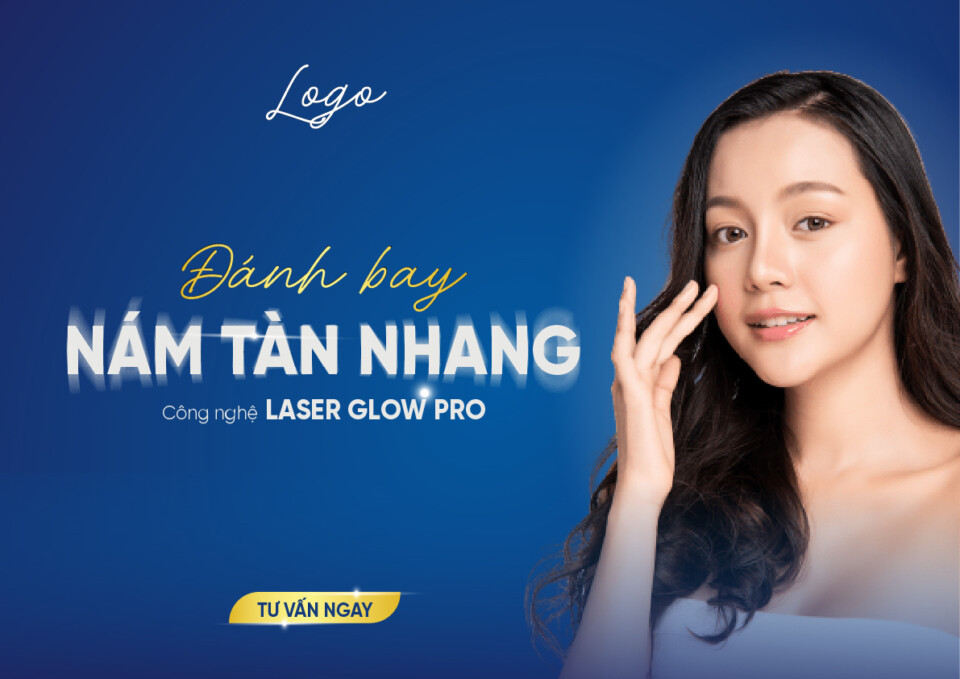
Combo font chữ Spa 1 kèm hiệu ứng đẳng cấp cho thiết kế ngành làm đẹpSức hút từ bộ Combo font chữ Spa 1 kèm hiệu ứng trong thiết kế hiện nayTrong ngành dịch vụ làm đẹp và chăm sóc sức khỏe tại Việt Nam, việc xây dựng hình ảnh thương hiệu chuyên nghiệp là yếu tố sống còn để thu hút khách hàng tiềm năng. Một Font Miễn Phí phù hợp không chỉ đơn thuần là công cụ hiển thị văn bản mà còn là ngôn ngữ thị giác truyền tải sự tinh tế và sang trọng. Chính vì vậy, Combo font chữ Spa 1 kèm hiệu ứng đã trở thành giải pháp tối ưu dành cho các nhà thiết kế đồ họa cũng như chủ doanh nghiệp muốn tạo nên sự khác biệt. Bộ sưu tập này được tuyển chọn kỹ lưỡng, tập trung vào các nét chữ thanh mảnh, bay bổng nhưng vẫn giữ được sự hiện đại cần thiết cho các ấn phẩm như menu spa, card visit, hay biển hiệu quảng cáo ngoài trời.Lý do nên lựa chọn font chữ Việt hóa cho ngành làm đẹpVấn đề lớn nhất khi sử dụng các bộ chữ quốc tế chính là lỗi hiển thị tiếng Việt, đặc biệt là các dấu thanh đặc trưng. Với Combo font chữ Spa 1 kèm hiệu ứng, mọi rào cản về kỹ thuật đã được loại bỏ hoàn toàn nhờ quá trình Việt hóa tỉ mỉ. Các đường nét được căn chỉnh sao cho dấu câu không bị đè lên chữ, giữ nguyên tính thẩm mỹ nguyên bản của thiết kế. Điều này giúp các bạn sinh viên ngành đồ họa hoặc những người mới bắt đầu có thể dễ dàng áp dụng vào bài tập thực hành hay dự án thực tế mà không cần tốn quá nhiều thời gian chỉnh sửa thủ công từng ký tự.Các đặc điểm nổi bật của Combo font chữ Spa 1 kèm hiệu ứngĐiểm độc đáo nhất của bộ sản phẩm này chính là sự tích hợp sẵn các lớp hiệu ứng đi kèm, giúp văn bản trở nên nổi bật và có chiều sâu hơn. Thay vì chỉ là những dòng chữ phẳng lỳ đơn điệu, Combo font chữ Spa 1 kèm hiệu ứng cung cấp các tùy chọn về đổ bóng, ánh kim (metallic) và độ nhám bề mặt. Những hiệu ứng này cực kỳ phù hợp để tạo ra các tiêu đề lớn trên banner khuyến mãi hoặc các bài đăng quảng cáo trên mạng xã hội. Khi kết hợp cùng tông màu pastel nhẹ nhàng hoặc vàng đồng sang trọng, bộ font này sẽ ngay lập tức nâng tầm đẳng cấp cho bộ nhận diện thương hiệu của bất kỳ thẩm mỹ viện nào.Ứng dụng thực tế của bộ font trong quảng cáo và in ấnTính ứng dụng cao là một trong những tiêu chí hàng đầu khi chúng tôi chia sẻ bộ sưu tập này đến cộng đồng. Bạn có thể sử dụng các kiểu chữ Script mềm mại cho tên thương hiệu để gợi cảm giác thư giãn, trong khi các kiểu Sans-serif hiện đại sẽ được dùng cho phần mô tả dịch vụ để đảm bảo sự rõ ràng, dễ đọc. Việc sử dụng đồng bộ Combo font chữ Spa 1 kèm hiệu ứng giúp tạo ra một mạch thiết kế xuyên suốt, giúp khách hàng dễ dàng nhận diện và ghi nhớ thương hiệu lâu hơn giữa hàng nghìn đối thủ cạnh tranh trên thị trường hiện nay.Tải và trải nghiệm bộ Combo font chữ Spa 1 kèm hiệu ứng hoàn toàn miễn phíChúng tôi luôn mong muốn mang đến những giá trị thiết thực nhất cho cộng đồng sáng tạo tại Việt Nam thông qua những tài nguyên chất lượng cao. Việc sở hữu Combo font chữ Spa 1 kèm hiệu ứng sẽ giúp bạn tiết kiệm đáng kể chi phí thiết kế mà vẫn đạt được hiệu quả thẩm mỹ mong muốn. Hãy bắt đầu thay đổi diện mạo cho các dự án của bạn ngay hôm nay bằng cách truy cập Font Miễn Phí, Font Việt Hóa, Combo font chữ Spa 1 kèm hiệu ứng để tải về phiên bản mới nhất. Chúc các bạn có thêm nhiều cảm hứng sáng tạo và gặt hái được nhiều thành công trong con đường sự nghiệp thiết kế chuyên nghiệp của mình.
Combo font chữ Spa 1 kèm hiệu ứng